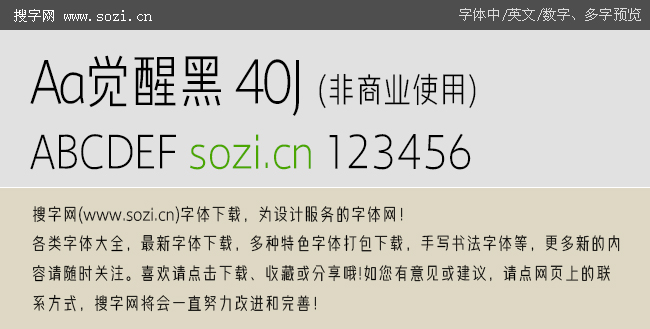
Aa覺醒黑 40J
搜字網(wǎng)給大家提供一款Aa覺醒黑 40J(非商業(yè)使用)中文字體下載,Aa覺醒黑是一款藝術黑體字體,字體簡潔大方,字形端正耐看,具有很好的視覺感,適合應用于藝術設計、平面宣傳設計、網(wǎng)頁設計、海報設計等應用(此字體為個人非商用版,商用可以聯(lián)系QQ:1006760504)。